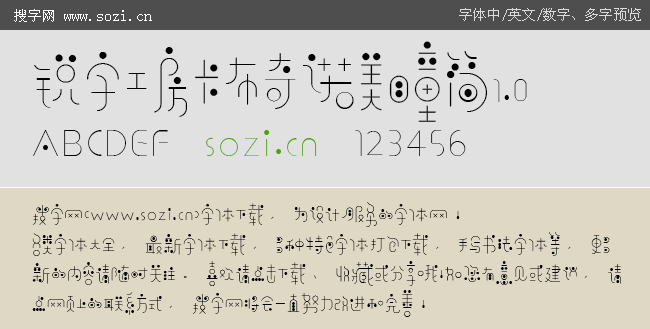
銳字工房卡布奇諾美瞳簡
搜字網(wǎng)提供一款非常藝術(shù)的銳字工房卡布奇諾美瞳簡下載,銳字工房卡布奇諾美瞳簡是一款字形呈卡通效果的銳字工房字體,該字體極具藝術(shù)感,非常有趣,適用于包裝印刷、廣告設(shè)計(jì)、平面設(shè)計(jì)、書籍報(bào)紙等領(lǐng)域。